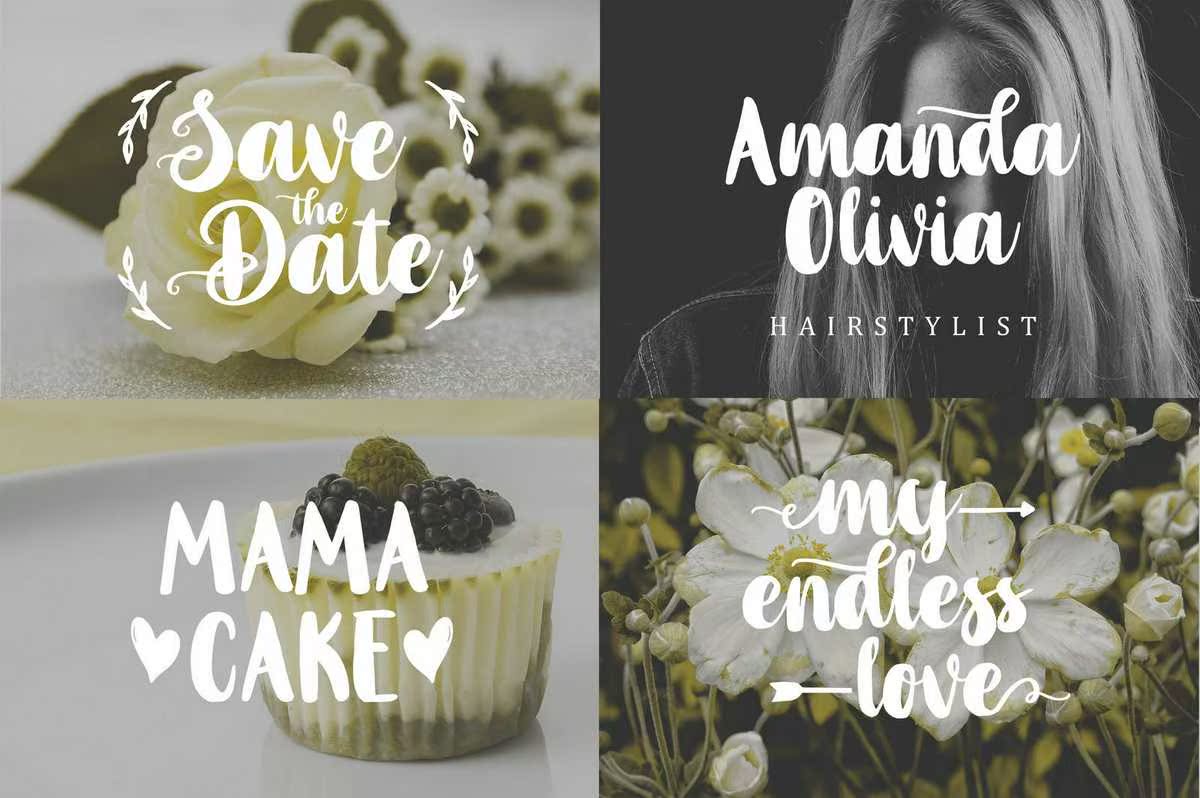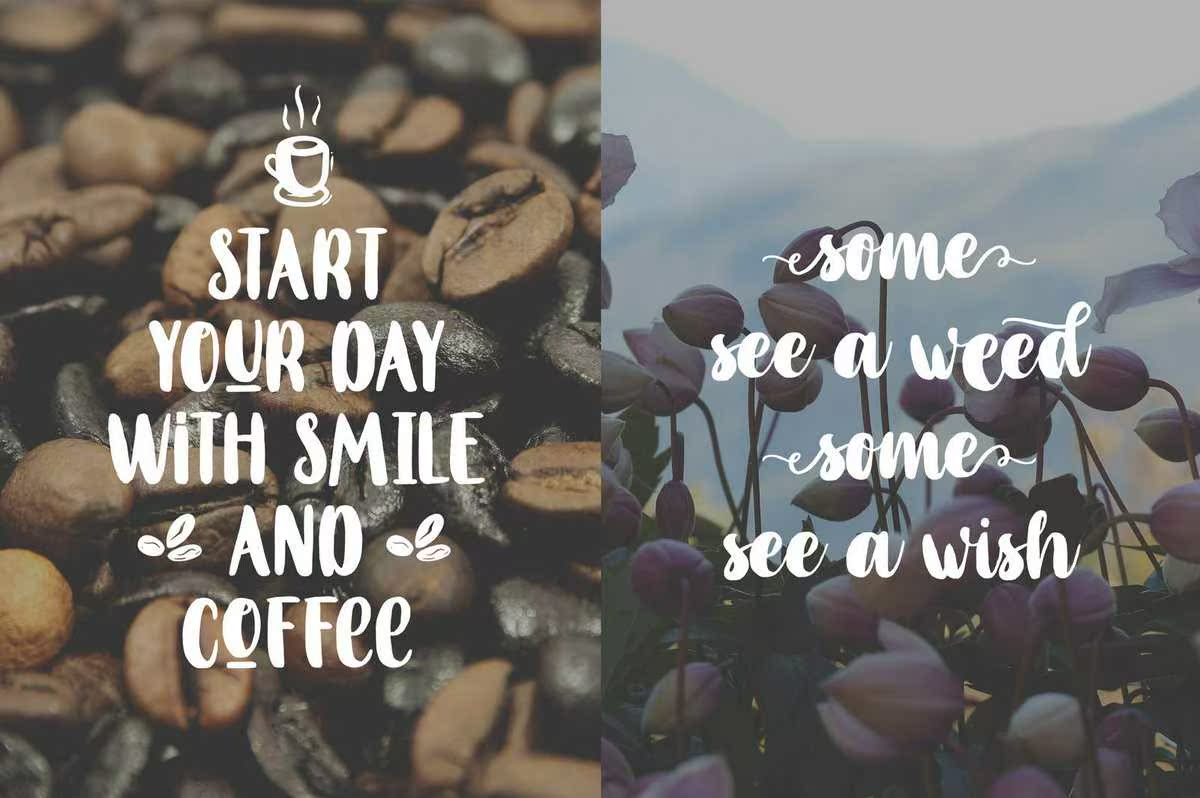
Mahoni是一种Old ScriptFont,它具有现代拼音风格所要求的一般手写字符。Mahoni具有一种字体风格,但您可以重新使用大写字母,这种字体将形成一个字符,看起来像两个不同的字体。适用于创建字体设计、圣诞卡、品牌、徽标、产品包装、邀请函、qoutes、t恤、,labelposteretc.Mahoni是一种Old ScriptFont字体,它们通常具有现代拼音风格所要求的手写字符。Mahonicome具有一种字体风格,但您可以重新使用大写字母,这种字体将形成一个字符,看起来像2个不同的字体。适合并适用于创建字体设计、圣诞卡、品牌、徽标、产品包装、邀请函、QOUTS、t恤、,labelposteretc。